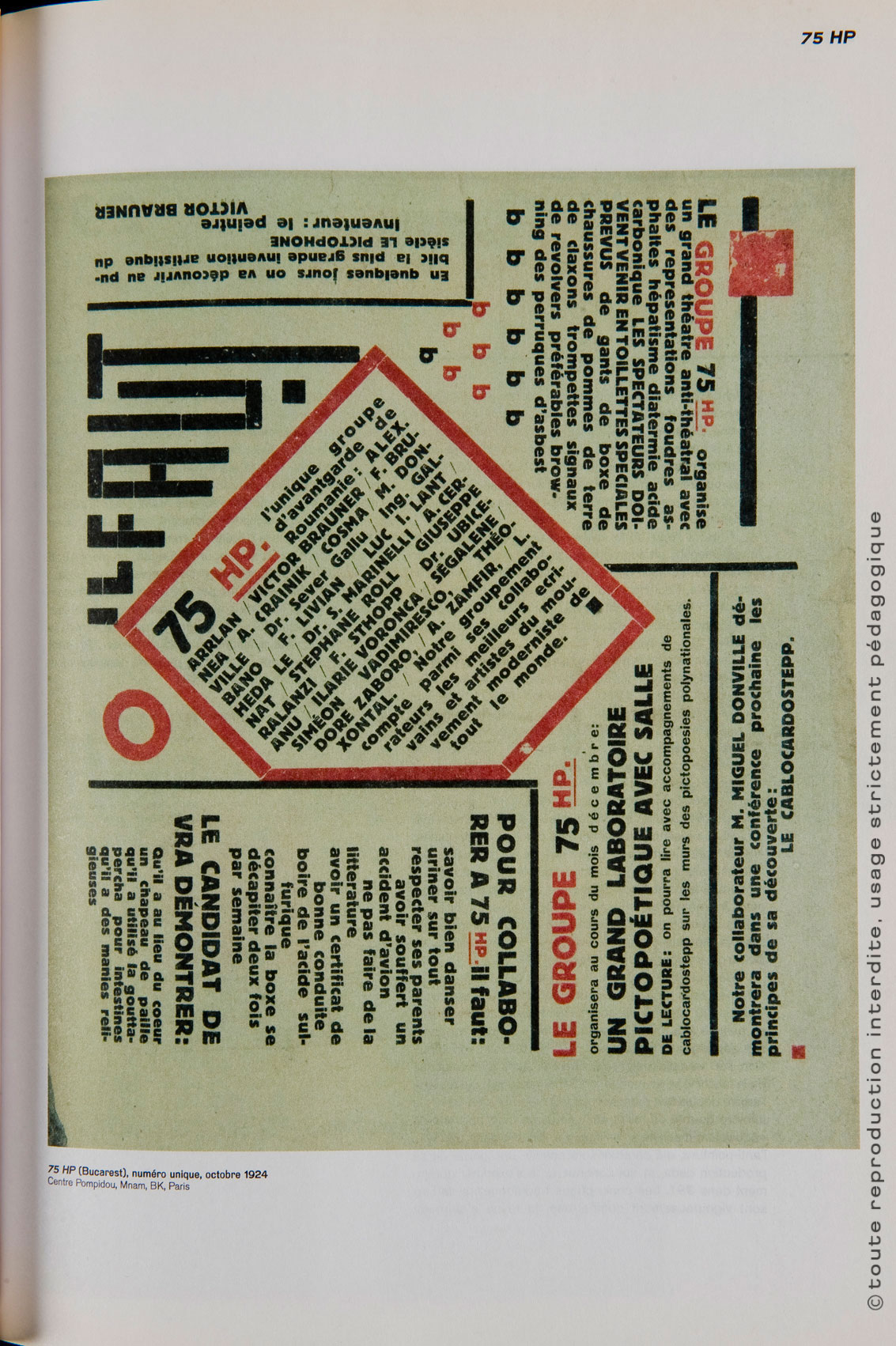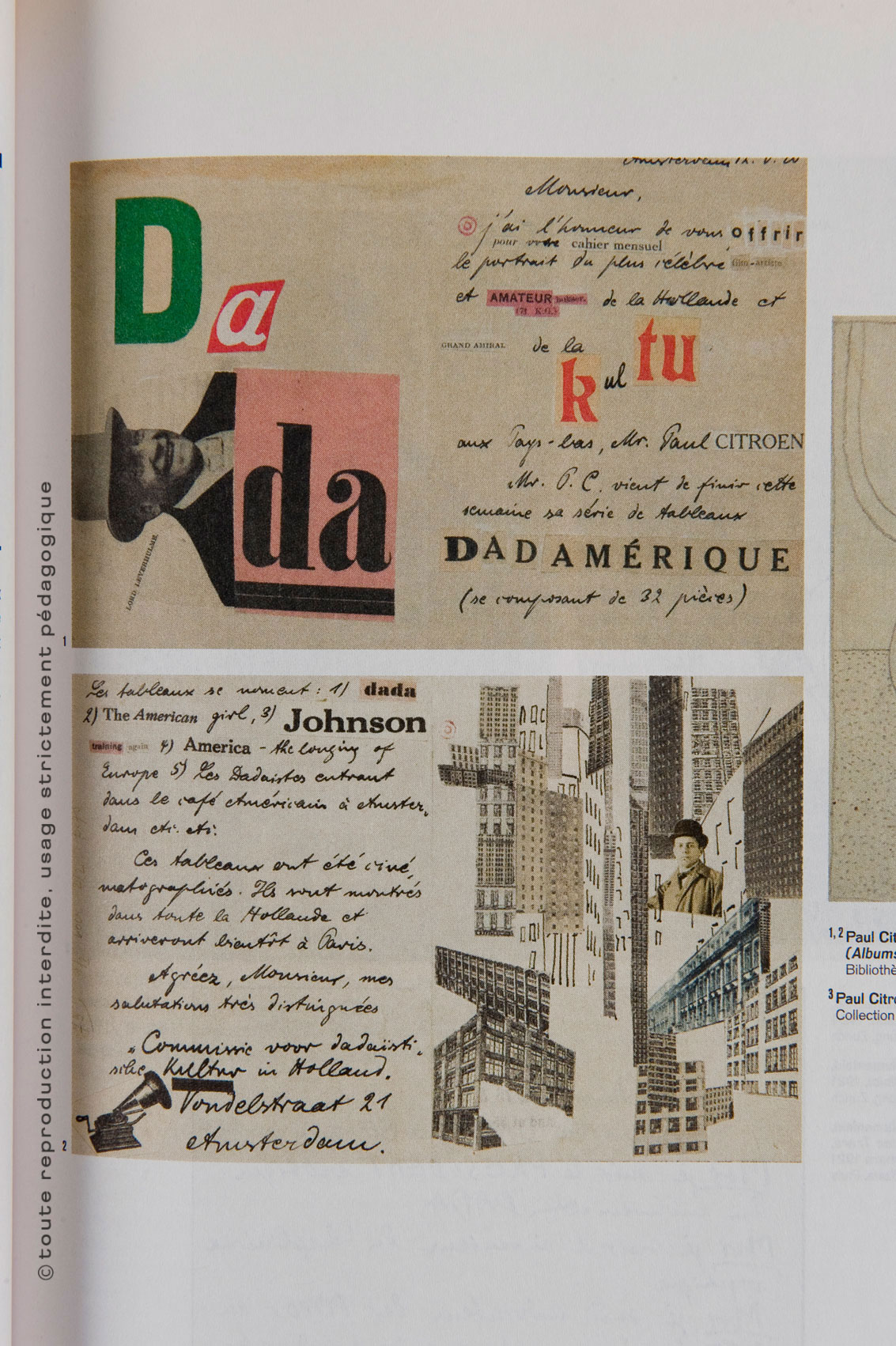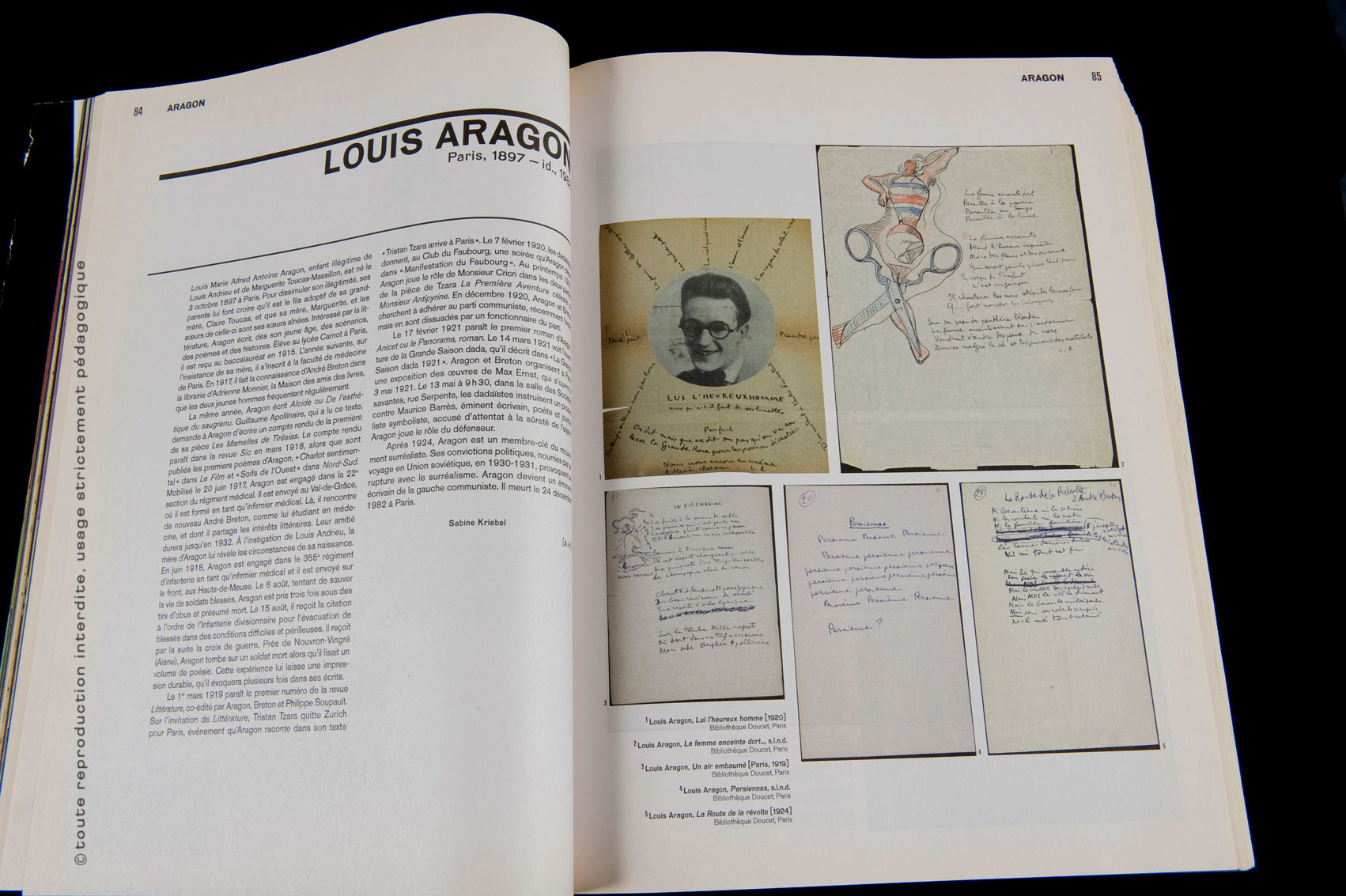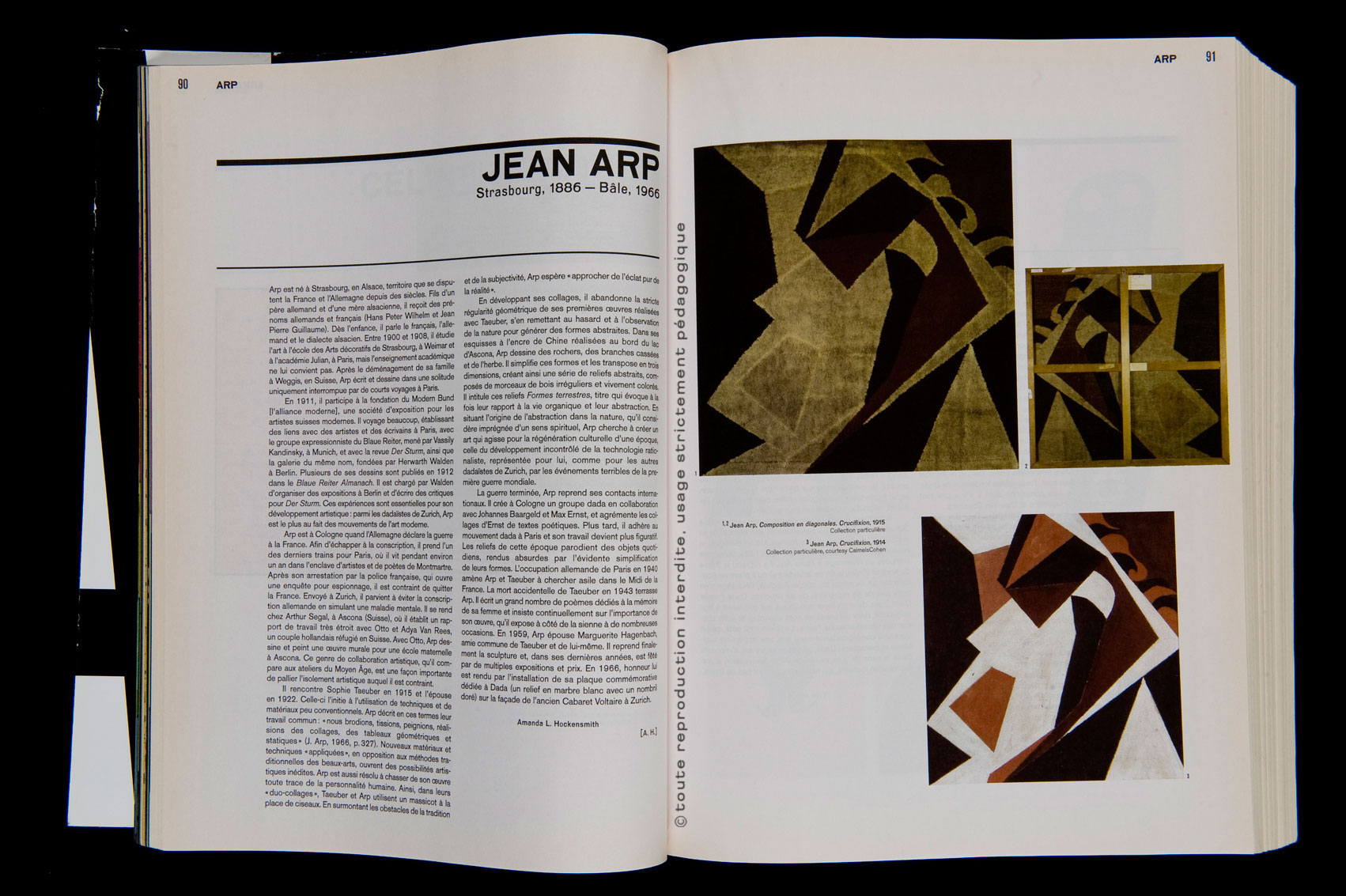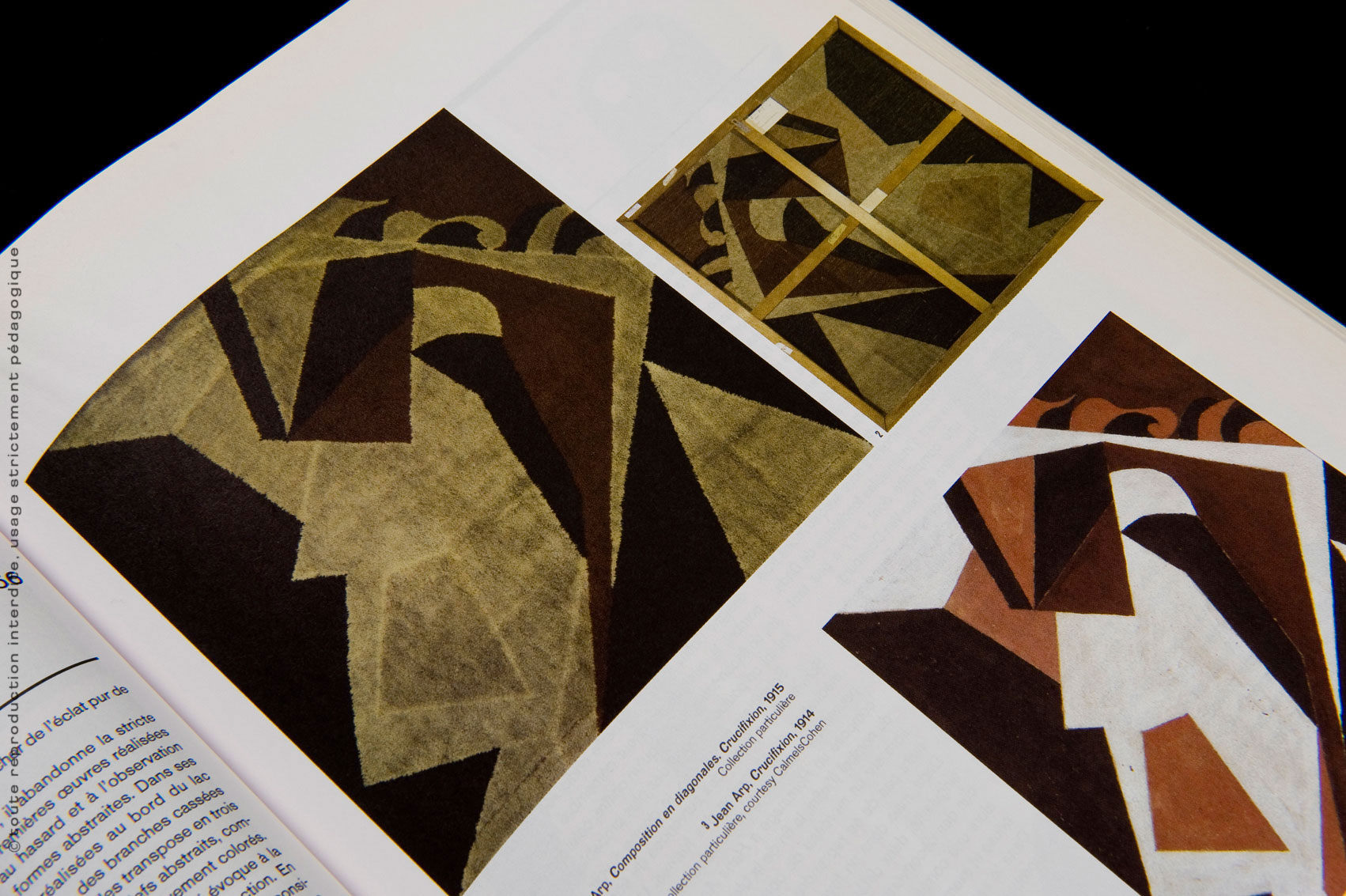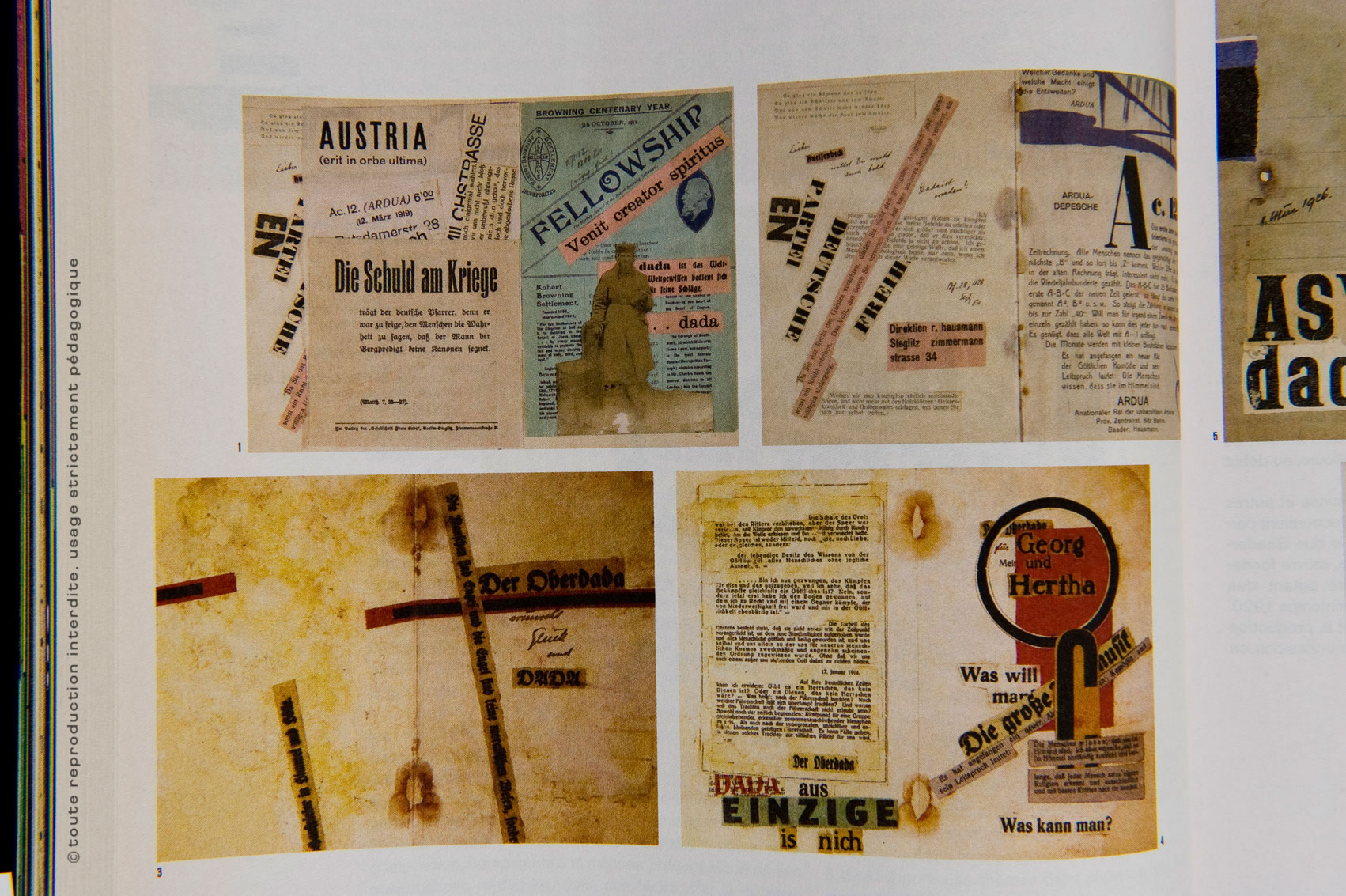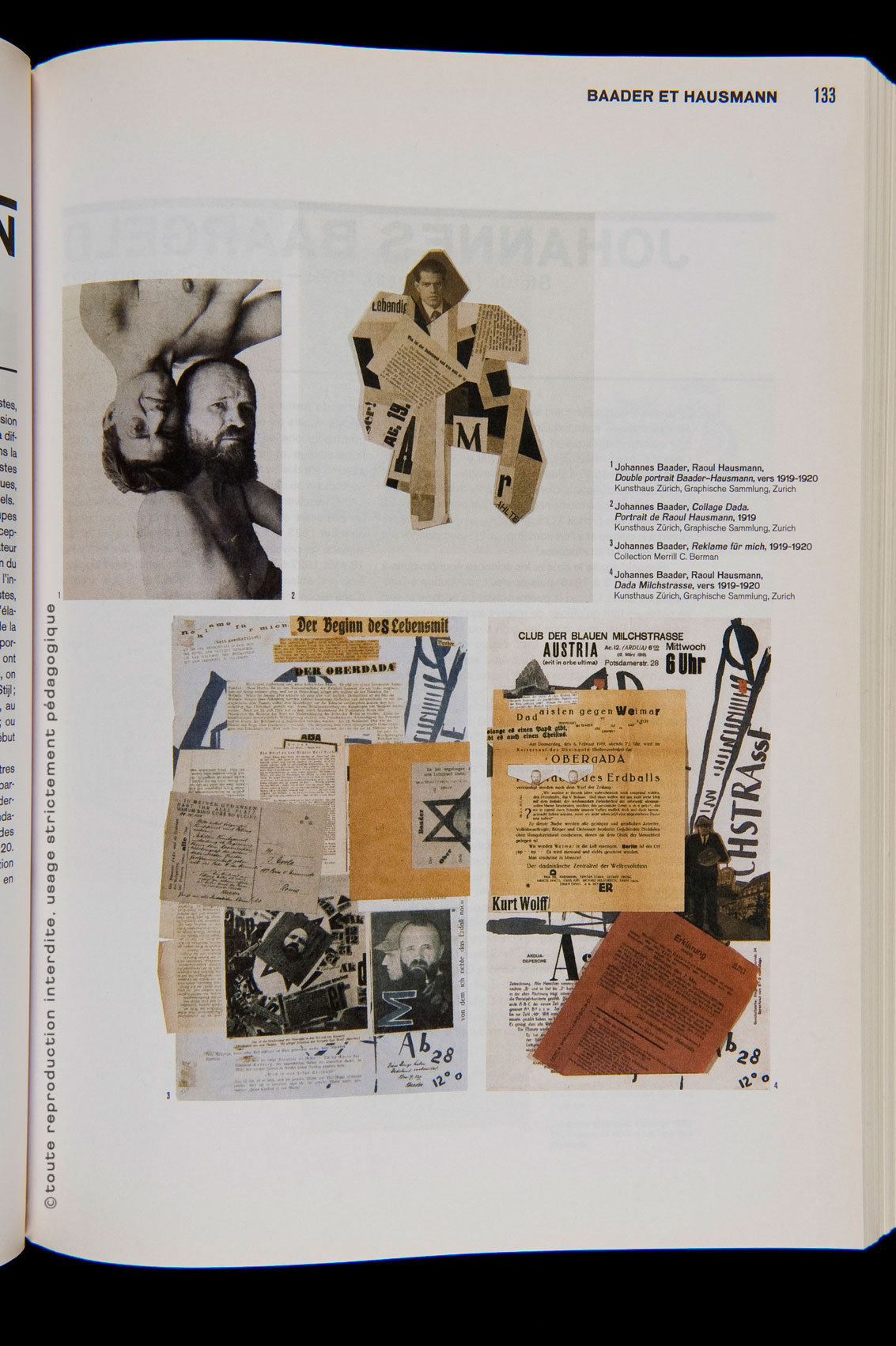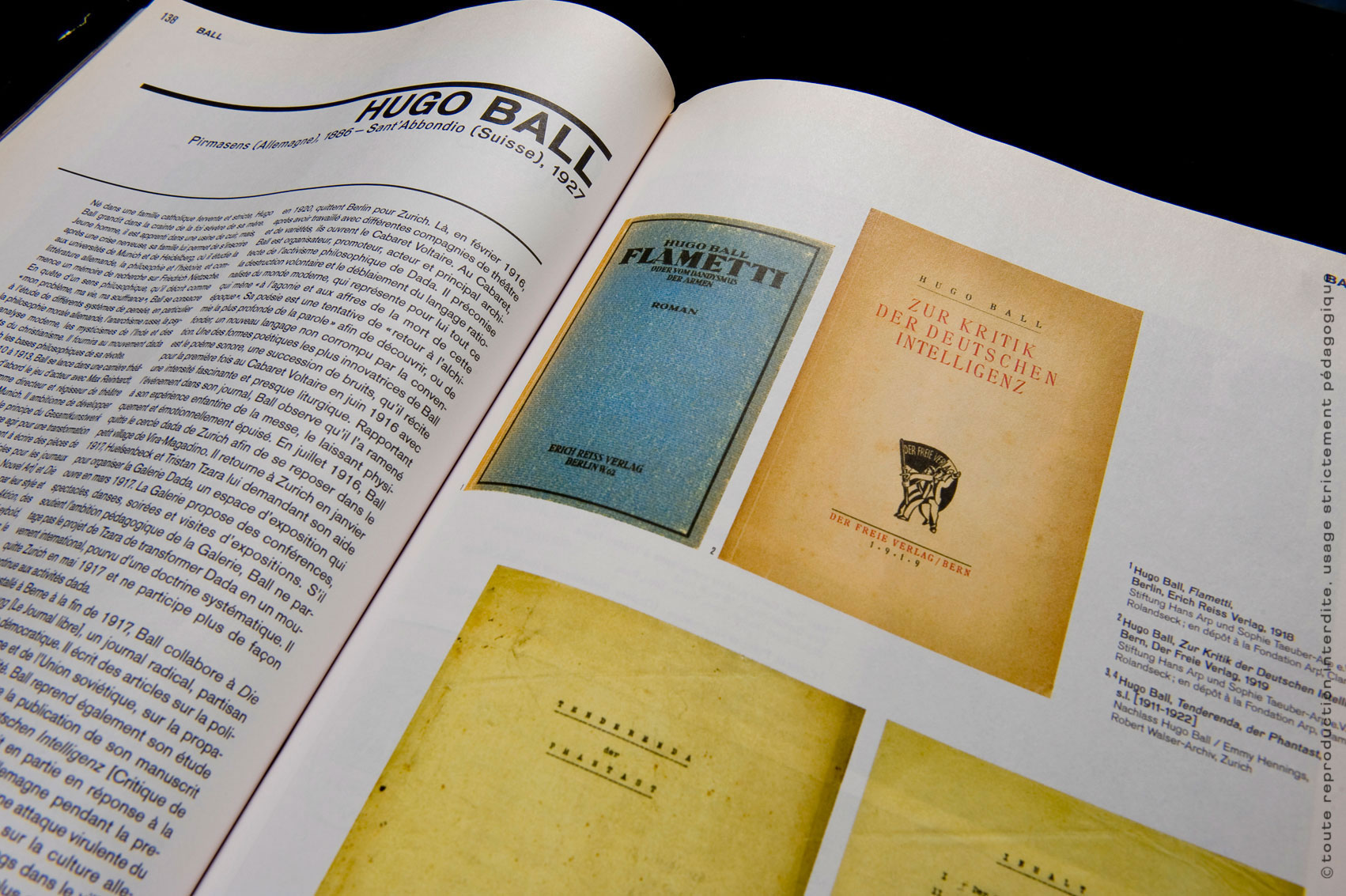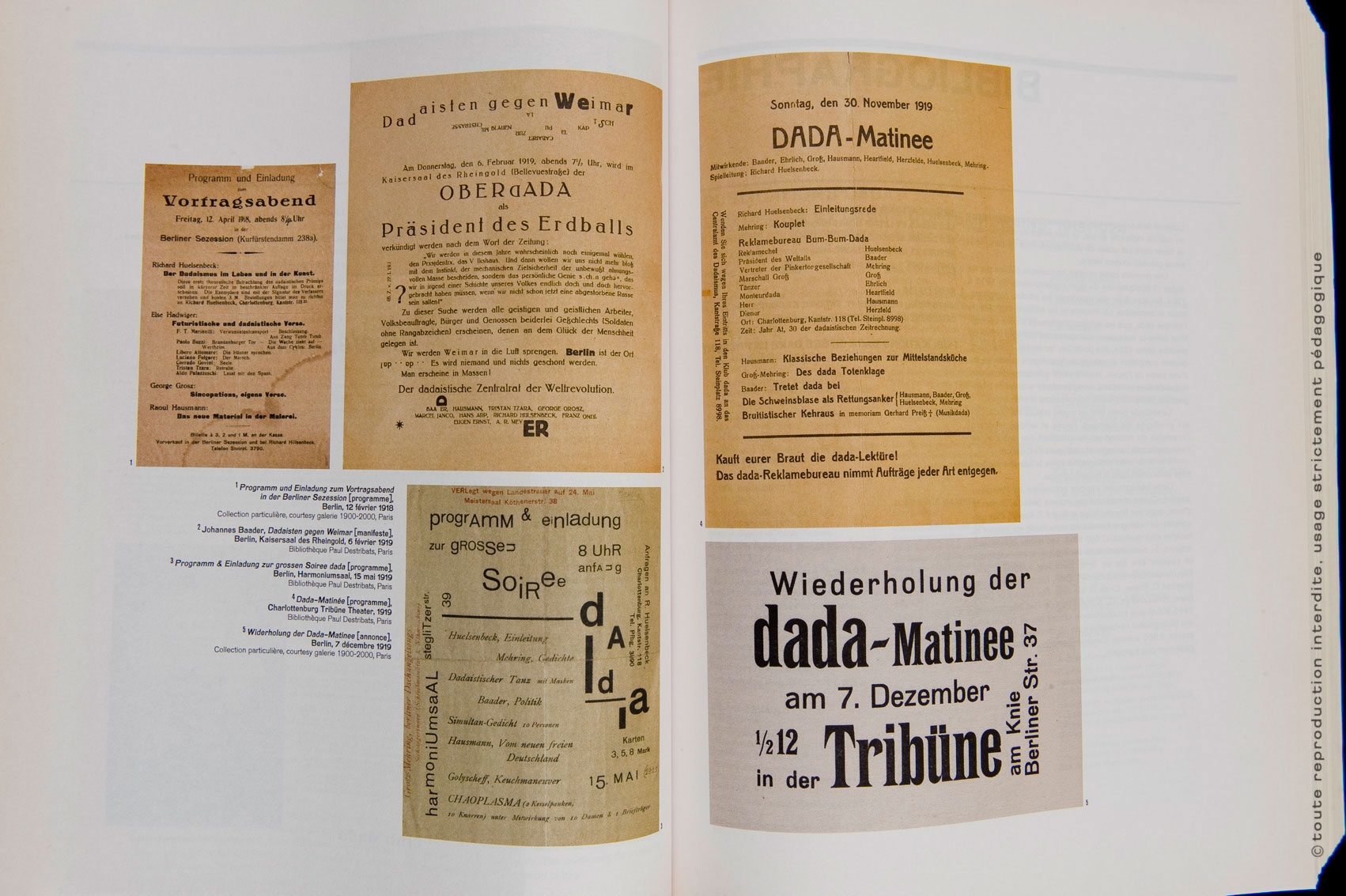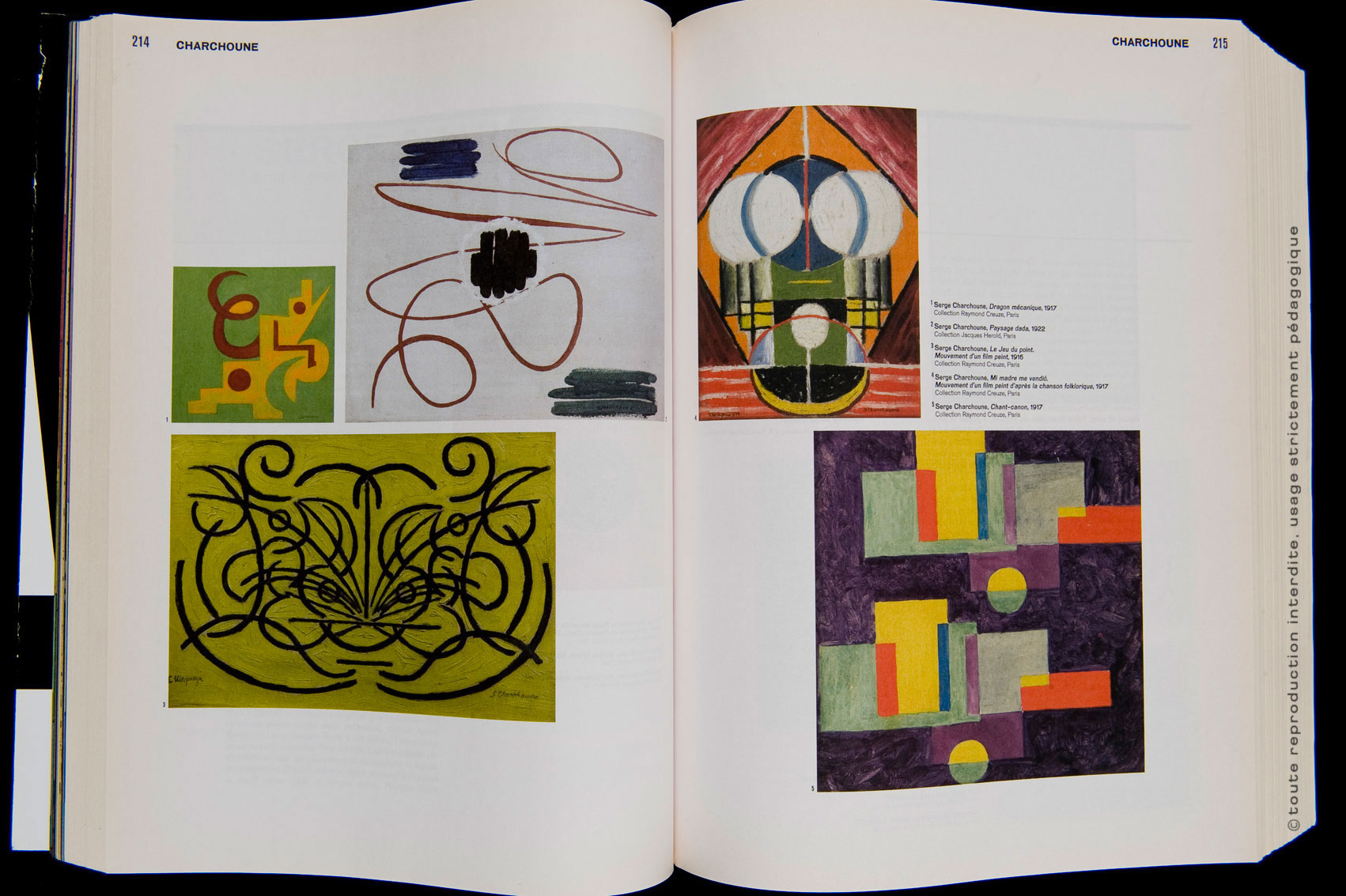
Le Mouvement DaDa ou la Transgression en marche 2
C’est en 2005 que le Musée Georges Pompidou organise une des plus grandes rétrospective que l’on ait consacré au mouvement DaDa, et à tous les artistes qui de près ou de loin s’en réclamaient.
Je me permets de publier ici les pages du catalogue qui fut alors édité par le Musée et qui représente l’un des plus beau travail qui ne fut jamais réalisé de mémoire de muséographe. À la fois chrono-logique et alphabétique, le livre retrace le cheminement d’une époque difficile puisqu’elle démarre un peu avant la Drôle de Guerre (14-18) et se prolonge un peu après.
De fait lorsqu’on étudie le mouvement DaDa on devrait toujours faire un parallèle avec deux autres mouvements simultanés, l’une en Russie avec le Constructivisme et l’autre en Allemagne à Weimar avec le Bauhaus. Trois attitudes, trois réponses différentes posées par les mêmes problématiques. Fins de régimes, montée de l’industrialisation, et crise de 29 annonciateur de bouleversements encore plus radicaux. Dans cette courte période de 1905 à 1920, le monde va basculer à l’est vers le bolchevisme et les idéaux d’un pouvoir populaire, au centre vers le nazisme avec les crimes humanitaires qu’on lui connaît.
Au centre de tout il y a la Suisse,
petit pays neutre et sans doute à l’abri, en toutes apparences des grandes révolutions qui jouxtent ses frontières. Et c’est là, dans une atmosphère plutôt bon enfant que naîtra le mouvement DaDa. Allez savoir, la bourgeoisie est capable de tant d’autodérision. Parce que là où la rigueur abstraite et à la fois construite des architectes du Bauhaus, là où les graphistes et photographes de la Russie née de la Révolution d’Octobre vont «changer le monde» et notre perception du monde, le DaDa va faire plus, il va installer le spectateur dans une transgression de sa perception.
Bousculer les lignes et les équilibres.
Renverser la gravité de la page et du sens des mots. Rien n’échappe au DaDa, poésie, graphisme, typographie, photographie, musique et arts plastiques. Chacune des expressions se retrouve non pas tête en bas mais «à coté». De coté si vous préférez. Histoire d’en rire ou de se moquer, histoire de provoquer, de déranger, de renverser les idées reçues. Mais alors que les deux autres mouvements vont procéder à une entreprise de démolition-reconstruction, le DaDa ne propose rien, ne reconstruit rien. La transgression pour la transgression. La transgression pour dénoncer, hurler contre l’absurde d’une société qui envoie ses enfants comme chairs à canon se faire démolir la gueule et le ventre. Transgression pour manifester l’angoisse des artistes devant le non sens d’un monde qui commence (seulement) une course effrénée vers la vitesse.
Plus vite, toujours plus vite.
Voici venir le temps des machines qui écrasent l’homme dans sa fragilité et l’artiste se révolte et envoie la typo, valser tête en bas ou de côté pour dire sa révolte d’artiste et d’homme… DaDa, Constructivisme et Bauhaus, c’est trois courants fondamentaux qui vont donc déterminer l’avenir de nos métiers, dont tous les graphistes un jour ou l’autre se revendiqueront.